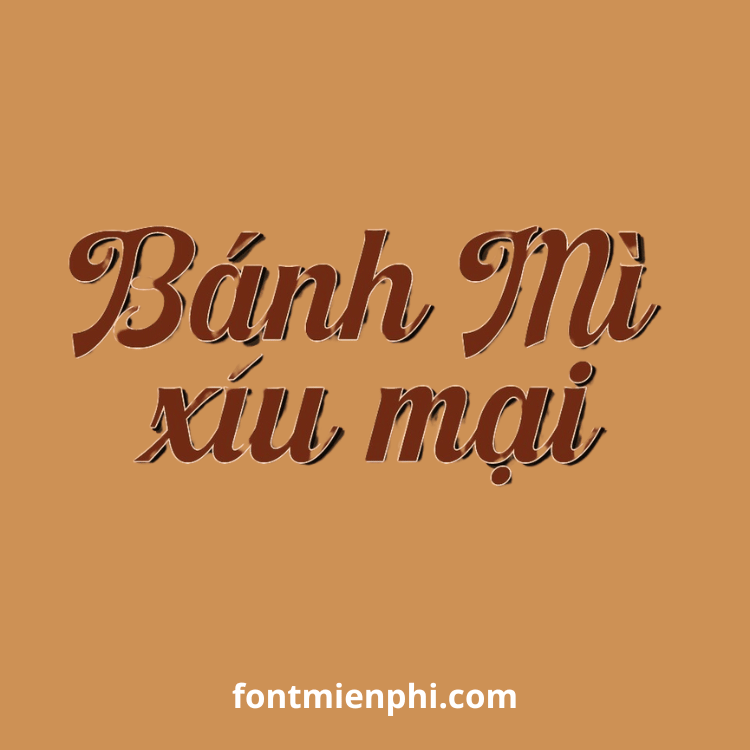
Font Việt hóa 1FTV VIP Ampher
Font Việt Hóa 1FTV VIP Ampher – Phong Cách Mạnh Mẽ, Đậm Chất Cá Tính
Font Việt hóa 1FTV VIP Ampher là một trong những font chữ nổi bật với phong cách mạnh mẽ, góc cạnh và đầy cá tính. Được thiết kế dành riêng cho các dự án cần sự độc đáo và ấn tượng, font chữ này là lựa chọn hoàn hảo cho thiết kế logo, game, poster, quảng cáo hoặc các ấn phẩm mang phong cách urban, street style.
Đặc điểm nổi bật:
✔ Hỗ trợ tiếng Việt đầy đủ – Đảm bảo rõ ràng, dễ đọc, phù hợp với mọi nội dung tiếng Việt.
✔ Phong cách góc cạnh, cá tính – Nét chữ đậm, sắc nét, tạo cảm giác mạnh mẽ và hiện đại.
Với 1FTV VIP Ampher, bạn có thể tạo ra những thiết kế đầy ấn tượng, phù hợp với phong cách gaming, thể thao, âm nhạc hoặc thương hiệu muốn thể hiện sự năng động.